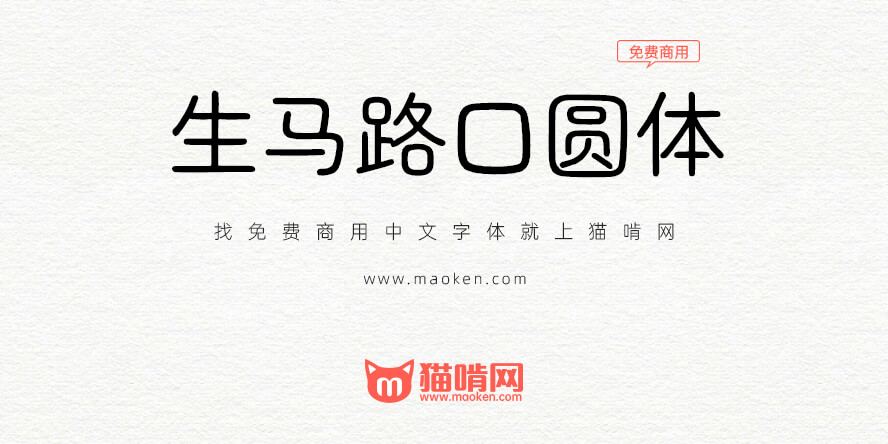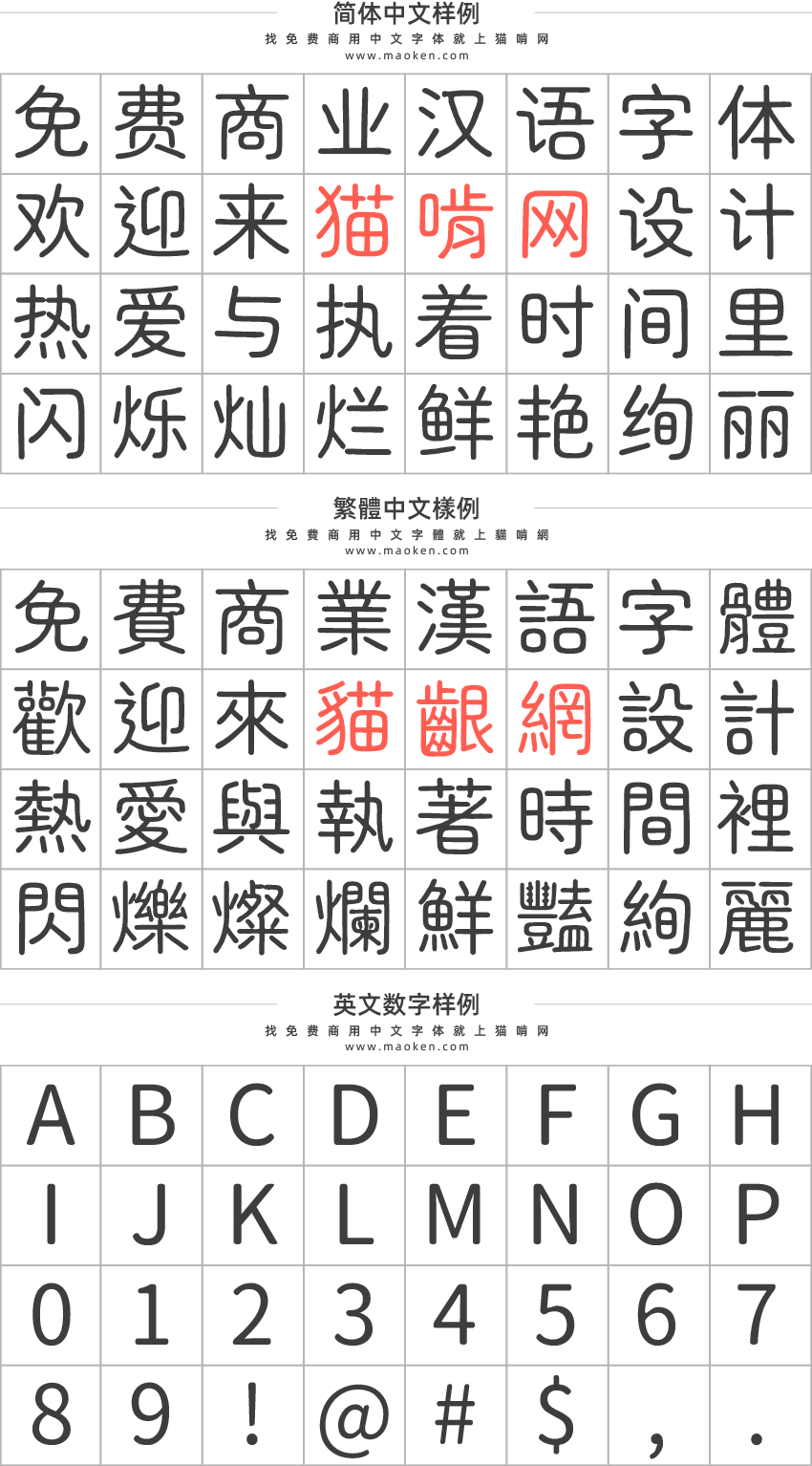
PS字体名:生馬路口圓體 | 字体版本:Version 1.001(2021/07/19) 更新记录 |
字体作者:Max(中国台湾) | 字体字重:1个 |
马路口圆体是Zen圆体字体的补字计划。与原作者的主要差异是调整部件写法、新增中文字、增加一些符号。可以免费商用,欢迎大家自由应用、自由优化、自由改作!
体验版:在完成较漂亮版本的补字前,在 raw 目录下有尚青的“生”的体验版本,“生马路口圆体”(Raw Maruko Gothic)是未经处理的版本,大多数的字应该不会怪怪的,欢迎回报有杂点或笔触分叉的字,小编会再找时重做。
正式版:目前缓慢地补字中…, 没有下载点。每天增加几个字,何时会有新的版本,只能随缘…,第一阶段是要完成4800个台湾常用字,初步是缺659字。
这个字体我好喜欢,就是有一点可惜了,行距太大,导致很多APP显示字体不齐(遮一半)
MIUI用户前来报道,中文标点可以改到正常位置嘛?全部居中感觉好奇怪,买了小米就没用第三方字体了,之前一直用的汉仪良品线,MIUI主题商店的汉仪良品线粗的太粗、细的太细,不然就花钱买了,这款是免费里最完美的字体了,求改一下中文标点 (^ω^)
这个是繁体字体,一般都是置中标点。
这字体好棒!希望能够增加更多字重
这个不是前天发的Zen圆体一样的吗?字体包是一样的呀
在这个字体基础上增加简体字
这个是台标笔形,原版是日标笔形。此外,这个字体是深度学习生成的,看起来有点粗糙。
英数改成基于思源黑体的狮尾圆体可还行🤣